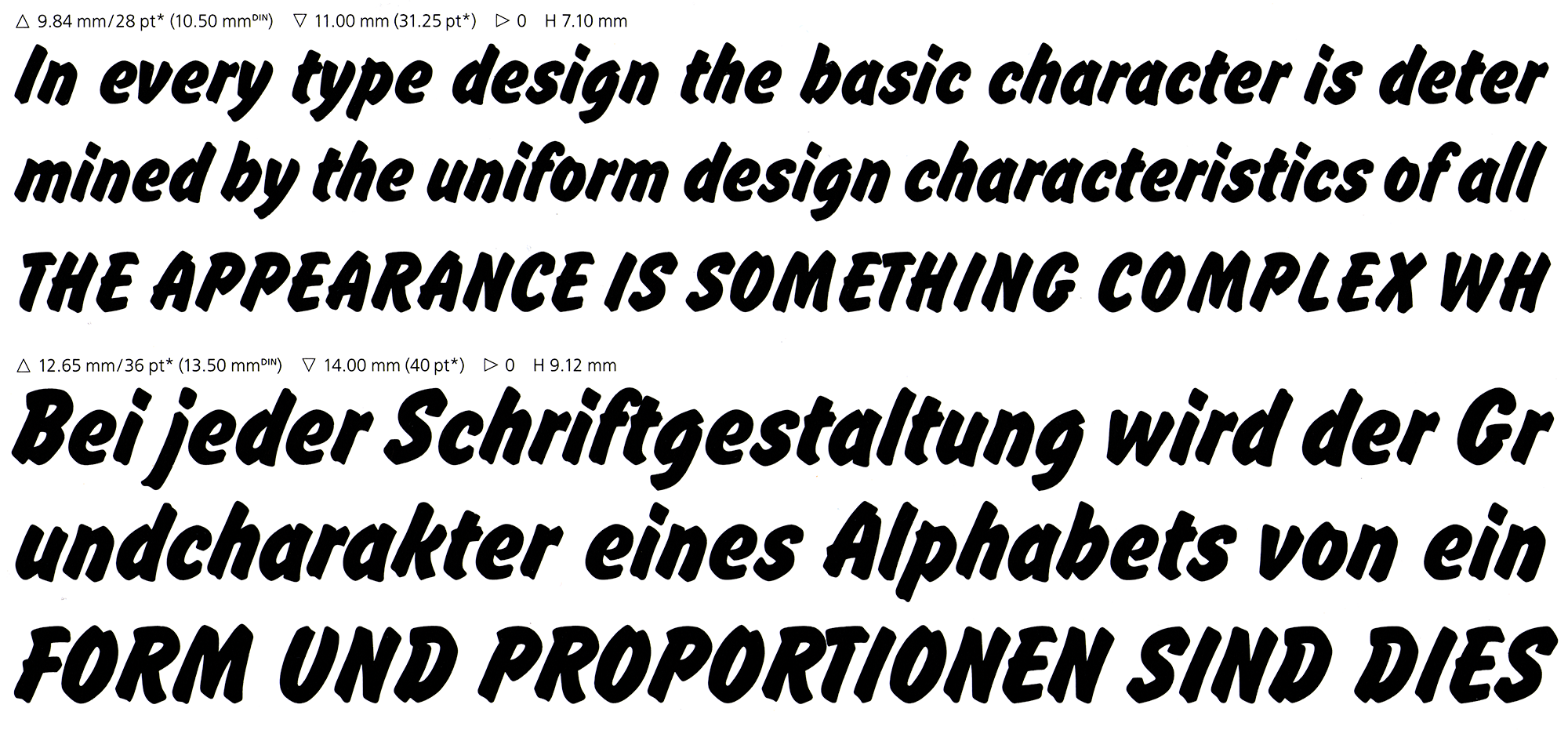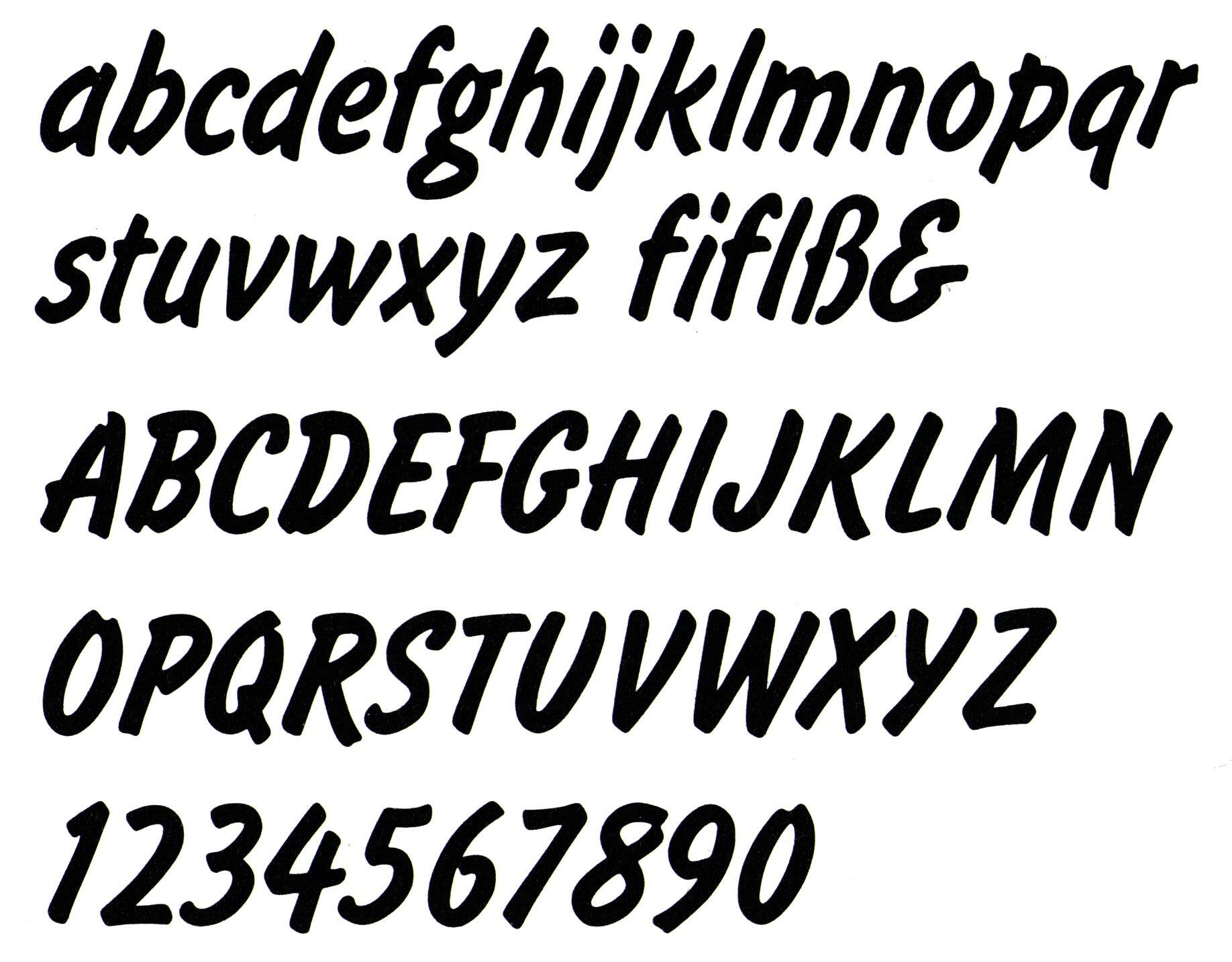
Die Flash von Edwin W. Shaar erschien ab 1939 bei Lanston Monotype und verfügt über zwei Strichstärken. Es erschienen zahlreiche Adaptionen für den Foto- und Digitalsatz. Der fettere Schnitt wurde und wird auch einzeln als »Okay« angeboten.
Unter dem Namen Flash gibt es Digitalisierungen von zum Beispiel Linotype, URW und Scangraphic.